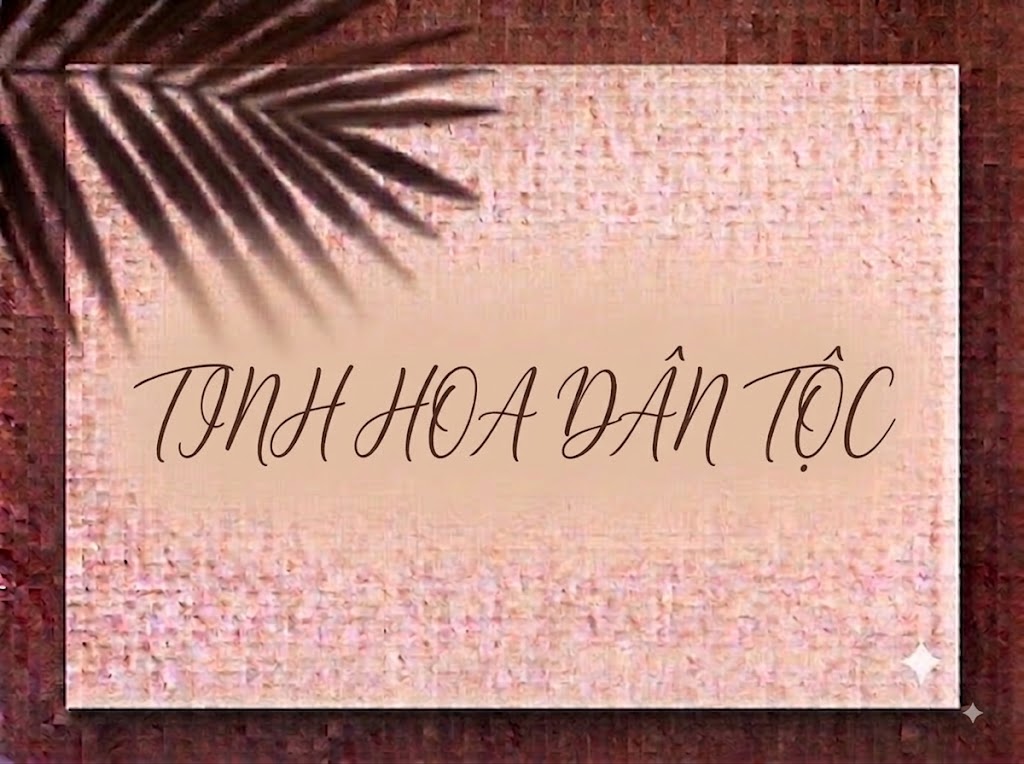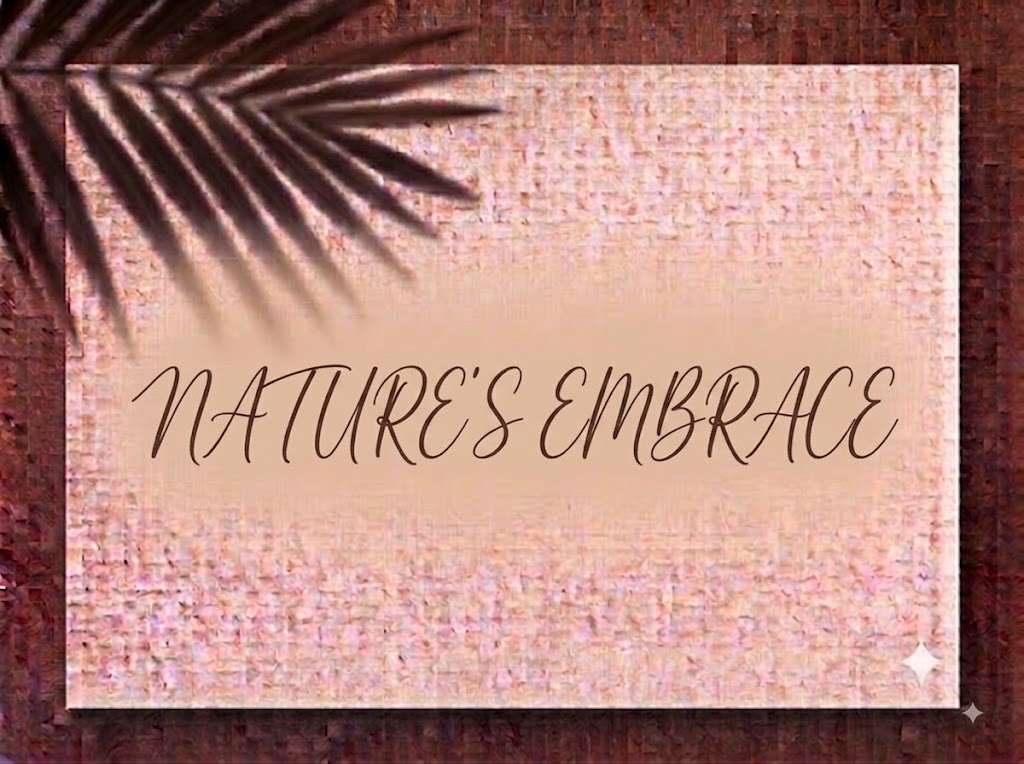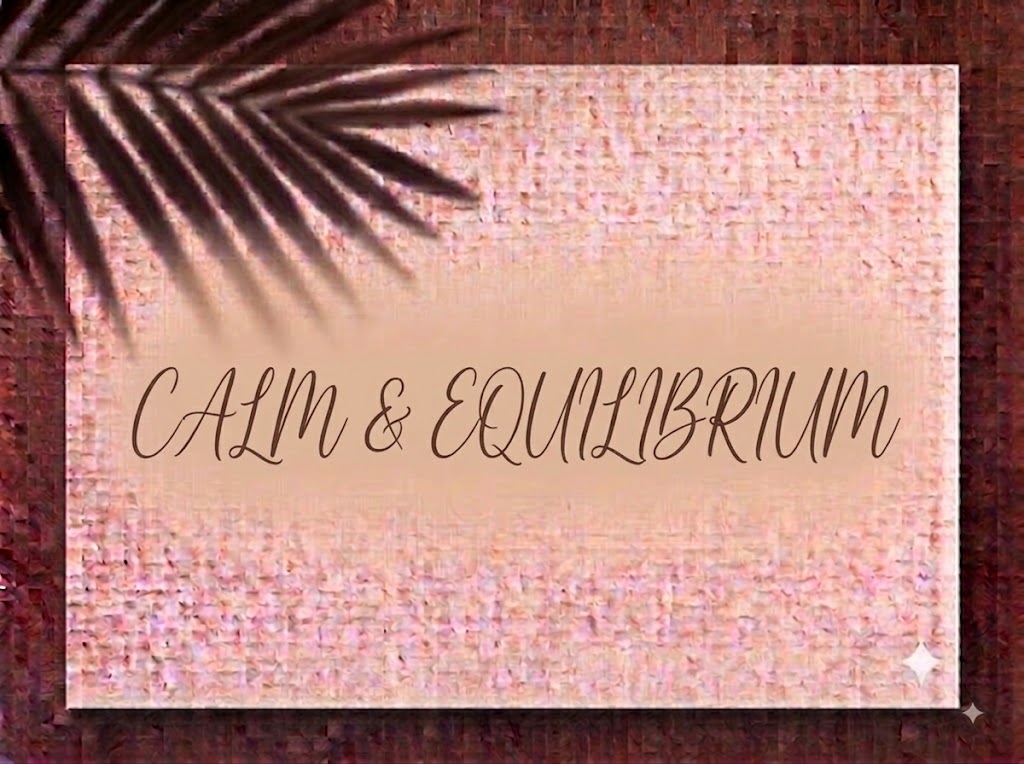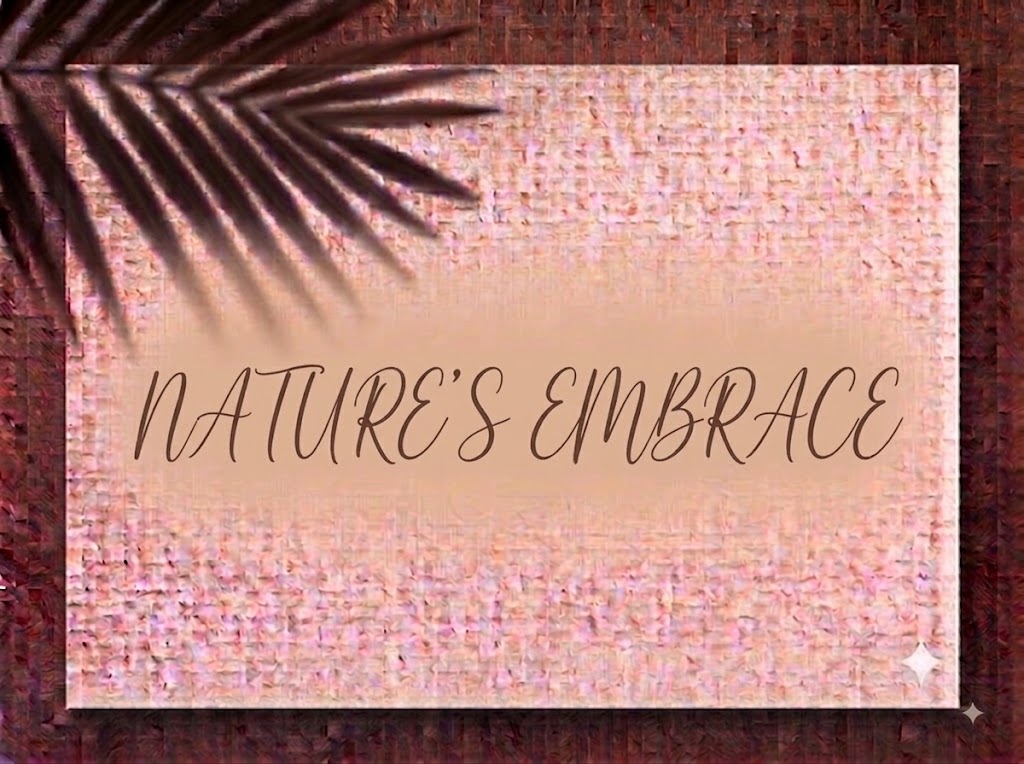
1FTV VIP Bentosa
Trong nghệ thuật thiết kế đồ họa, đặc biệt là các lĩnh vực liên quan đến cưới hỏi, mỹ phẩm, thời trang và lifestyle, những bộ phông chữ thư pháp phương Tây (Calligraphy/Script) uốn lượn mềm mại luôn là chìa khóa tạo nên sự kiều diễm, lãng mạn. Một dòng tiêu đề viết tay tinh tế không chỉ mang lại cảm xúc chân thành mà còn nâng tầm sự sang trọng cho toàn bộ ấn phẩm.
Nếu bạn đang tìm kiếm một phông chữ Calligraphy sở hữu nét chữ nối mềm mại, tự nhiên để làm thiệp cưới, menu tiệc, logo thương hiệu hay tiêu đề video ngắn, font 1FTV VIP Bentosa chính là sự lựa chọn vô cùng tuyệt vời.
Giới thiệu về font 1FTV VIP Bentosa
Font 1FTV VIP Bentosa là bộ chữ trang trí dạng viết tay (cursive script) mang phong cách Calligraphy hiện đại, nổi bật với sự kết hợp giữa nét thanh nét đậm tự nhiên cùng nhịp điệu chữ bay bổng:
Tên phông chữ: 1FTV VIP Bentosa
Được hoàn thiện kỹ lưỡng trên chuẩn OpenType, phông chữ đem lại khả năng hiển thị vô cùng mượt mà. Bạn có thể tự tin phóng lớn chữ trên các ứng dụng thiết kế đồ họa chuyên nghiệp hay phần mềm dựng video mà không lo bị vỡ nét hay dính nét.
Đặc điểm nổi bật của phong cách thiết kế VIP Bentosa
Sức hút thị giác của font 1FTV VIP Bentosa đến từ dáng chữ mềm mại và cảm giác viết tay đầy chất thơ:
Nét chữ uốn lượn mềm mại: Sự luân chuyển giữa đường nét mảnh mai và các nét nhấn đậm dịu dàng tạo cảm giác uyển chuyển, thanh thoát như nét bút mực thủ công.
Đường vươn cao (Ascenders & Descenders) kiều diễm: Phần đuôi và đầu của các ký tự như
f,g,j,k,p,q,y,zđược kéo dài uốn cong nghệ thuật, giúp câu tiêu đề có chiều sâu và nhịp điệu sinh động. -
Hỗ trợ đồng bộ chữ hoa và chữ thường: Bộ chữ cái in hoa cách điệu ấn tượng kết hợp cùng hệ thống chữ thường nối nét tự nhiên, giúp các designer dễ dàng tạo nên những cụm chữ headline thu hút.
Khoảng cách giữa các chữ (kerning) và liên kết nét được tính toán chuẩn xác, giúp các đường uốn lượn khi nối liền nhau vô cùng tự nhiên, không bị hở hay dính rối.
Tích hợp trọn vẹn bộ chữ cái hoa – thường, dãy chữ số 0-9 phom dáng mềm mại cùng hệ thống ký tự đặc biệt, dấu câu thông dụng.
Bản Việt hóa chuẩn chỉnh giúp bạn hoàn toàn yên tâm thiết kế các văn bản tiếng Việt có dấu phức tạp mà không gặp lỗi nhảy font hay mất ký tự.
Hình ảnh demo thực tế của font 1FTV VIP Bentosa
Khả năng hiển thị của phông chữ này được tối ưu rất tốt trên nhiều tỷ lệ kích thước khác nhau:
Kích thước nhỏ (12pt – 24pt): Cấu trúc nét thanh thoát giúp các câu chữ ngắn và dãy số vẫn hiển thị rành mạch trên giao diện màn hình di động.
Kích thước lớn (36pt – 72pt): Đây là đất diễn lý tưởng nhất để 1FTV VIP Bentosa phô diễn toàn bộ sự kiêu sa, lãng mạn và nét uốn lượn nghệ thuật, tạo tác động thị giác vô cùng tinh tế.
Ứng dụng trong thiết kế đồ họa và làm video
Sở hữu nét cá tính lãng mạn và kiều diễm, font 1FTV VIP Bentosa mở ra không gian ứng dụng phong phú:
Thiết kế Thiệp cưới & Sự kiện cao cấp: Lựa chọn hoàn hảo để viết tên chú rể – cô dâu trên thiệp cưới, thiệp sinh nhật, menu tiệc cưới, thiệp cảm ơn hay bảng Welcome sự kiện.
Video ngắn (TikTok, Reels, Shorts): Dáng chữ Calligraphy hiển thị rất thu hút trên khung hình đứng tỷ lệ 9:16. Cực kỳ ăn nhập với các video vlog đời sống, storytelling, thơ ca, làm đồ handmade hay clip phong cách lãng mạn.
Nhận diện thương hiệu Cửa hàng & Mỹ phẩm: Thích hợp làm logo dạng chữ viết tay, bao bì nến thơm, nước hoa, cửa hàng hoa tươi, tiệm bánh ngọt hay thương hiệu váy cưới.
Ảnh thu nhỏ YouTube (Thumbnail): Vũ khí tuyệt vời cho các kênh làm nội dung về âm nhạc Acoustic, Lofi Chill, Podcast trải lòng hay vlog du lịch nhờ giao diện ấm áp và nghệ thuật.